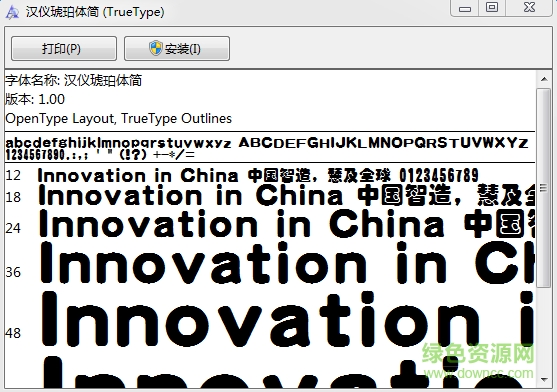
hyo1gj是什么字體?hyo1gj就是漢儀琥珀體簡(jiǎn)體,這款字體線條圓潤(rùn)流暢,外形飽滿大氣,清晰易讀,具有美感,即實(shí)用又不失藝術(shù)性,需要的朋友快來(lái)下載收藏吧!
hyo1gj字體特點(diǎn)
hyo1gj字體新穎活潑,結(jié)構(gòu)錯(cuò)落有序,粗而不重,胖而不臃,適用于書(shū)、報(bào)、雜志和各種印刷品的標(biāo)題及廣告字體!
漢儀琥珀體亮點(diǎn)
柔滑細(xì)膩,強(qiáng)壯有力,清晰醒目,美麗可愛(ài)等;
華文琥珀給人以多個(gè)筆畫(huà)拼湊、銜接在一起、富含層次感的感覺(jué);
美觀、清晰、醒目,給人的感覺(jué)既是柔滑細(xì)膩的又是粗壯有力的,確實(shí)稱得上“漂亮”字體!